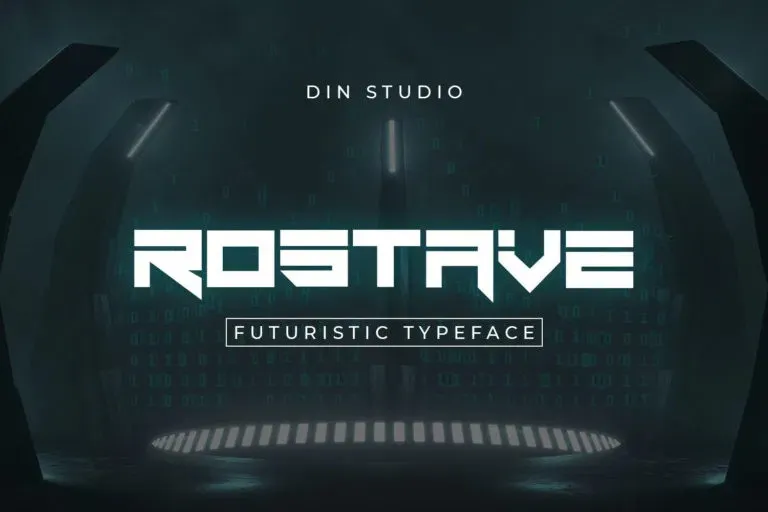
A Rostave Font é uma nova opção para designers que desejam adicionar um toque moderno e inovador a seus projetos visuais. Lançada pelo Din Studio, esta tipografia display se destaca por sua proposta diferenciada e futurista. Com linhas leves e curvas elegantes, Rostave atua como um catalisador de inspiração para qualquer projeto que busque uma sensação de modernidade e inovação. Ideal tanto para aplicações digitais quanto impressas, a fonte complementa perfeitamente o estilo de projetos futuristas ou visionários. Seja você um designer gráfico profissional ou iniciante, Rostave oferece a oportunidade de criar visualizações que se destacam em qualquer plataforma digital ou impressa. Não deixe seu trabalho de lado por falta de uma fonte com essa personalidade vibrante e moderna. Descubra o poder da Rostave Font.